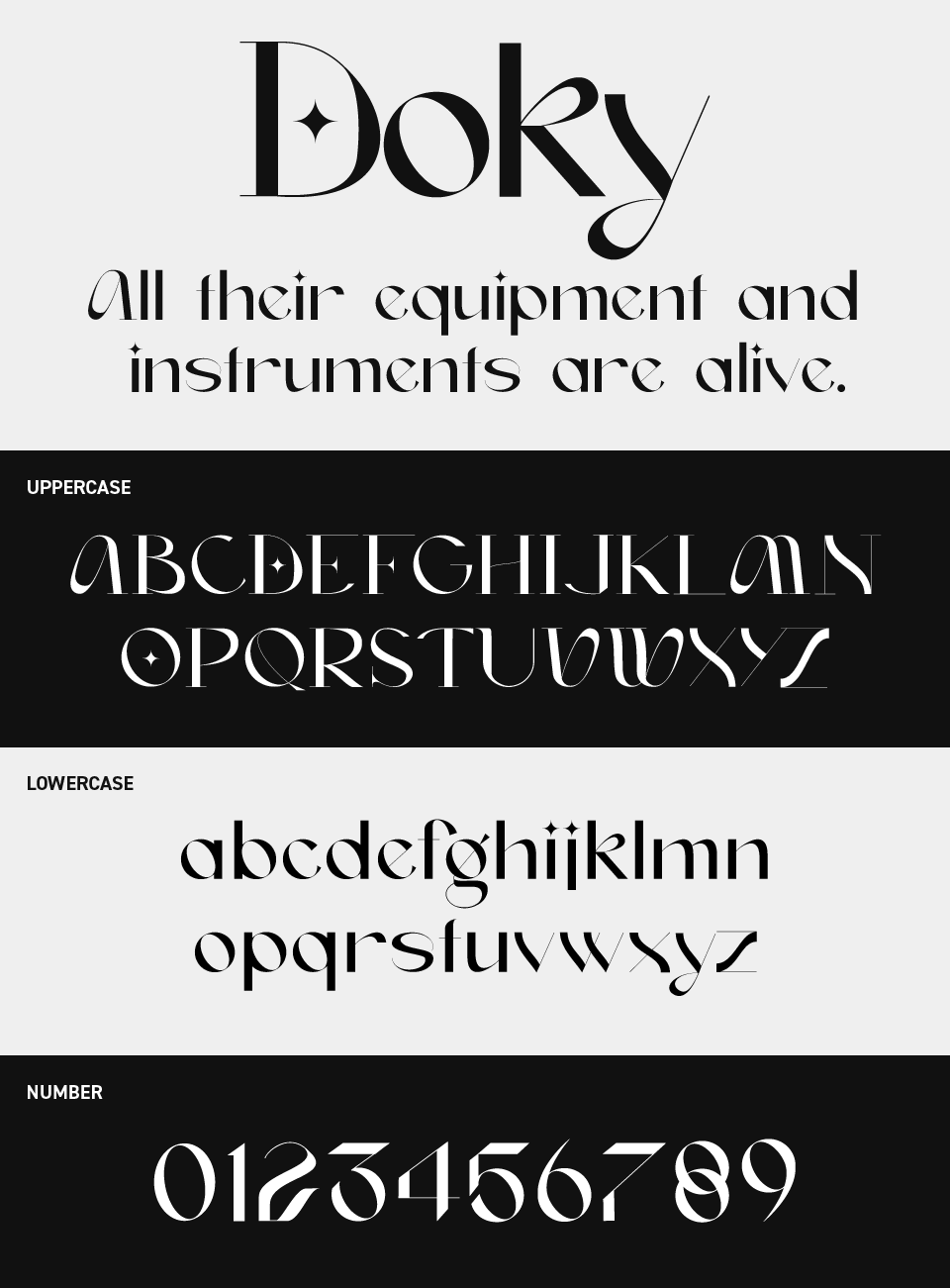
Dokyフォントは、曲線がやさしく揺れ、星の装飾がさりげなく光る、おとぎ話のようなムードを持つフォントです。
全体的に軽やかで、ふわっと空中を舞うような雰囲気が魅力です。ちょっとした星の装飾もアクセントになっており可愛らしいです。
甘すぎず、大人っぽさも感じさせる繊細なデザインは、ファッションやコスメ系のデザインとも相性抜群。ロマンチックな印象を加えたいときに重宝するフォントです。